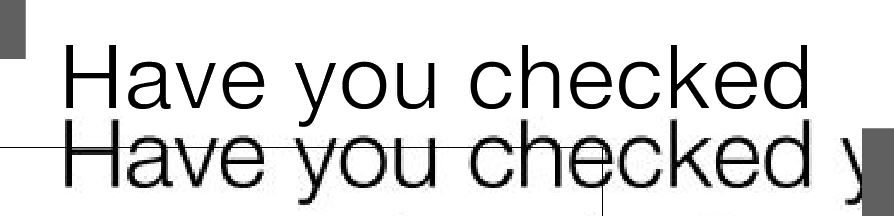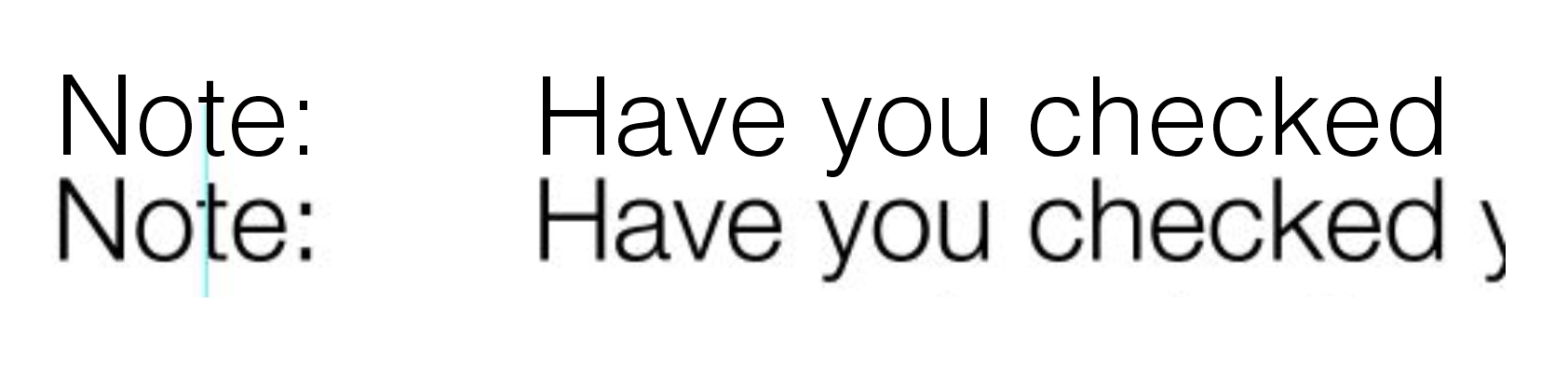
dilann Well-known member Jul 6, 2018 68,057 167,933 113 එකමත් එක රටක Sep 8, 2020 #21 Microsoft Sans Serif Helvetica Neue Regular Last edited: Sep 8, 2020 Reactions: D_Mad, SuperX, The Kingslayer and 1 other person
Heshan Daminda Well-known member Mar 13, 2009 46,421 1 101,337 113 34 Kalutara Sep 8, 2020 #22 Helvetica light nemeida Reactions: D_Mad and The Kingslayer
Gonawala_GUNE Well-known member Jun 21, 2020 3,111 7,983 113 Kandy Sep 8, 2020 #23 dilann said: Helvetica Neue Regular View attachment 92203 Click to expand... මේක හරි වගේ බන් මොකද ගොඩක් ඒවගේ y අකුර වෙනස්. මේකේ සමානයි. Reactions: D_Mad
dilann said: Helvetica Neue Regular View attachment 92203 Click to expand... මේක හරි වගේ බන් මොකද ගොඩක් ඒවගේ y අකුර වෙනස්. මේකේ සමානයි.
vectorizer Well-known member Jan 1, 2009 444 603 93 Sep 8, 2020 #24 Swiss font family එකේ වගේ https://www.swisstypefaces.com/fonts/suisse/#font Reactions: D_Mad
signshop Well-known member May 30, 2011 12,282 9,147 113 Dubai Sep 8, 2020 #25 meka Font eka Helvetica LT Light meka hari giye nathnam Helvetica set ekama try karala balapan. me Helvetica font Family eke font ekak Reactions: D_Mad and dilann
meka Font eka Helvetica LT Light meka hari giye nathnam Helvetica set ekama try karala balapan. me Helvetica font Family eke font ekak
pathaleiretta Well-known member Aug 18, 2015 9,323 21,357 113 Sep 8, 2020 #26 Basic Commercial Light WhatFontIs.com Reactions: D_Mad